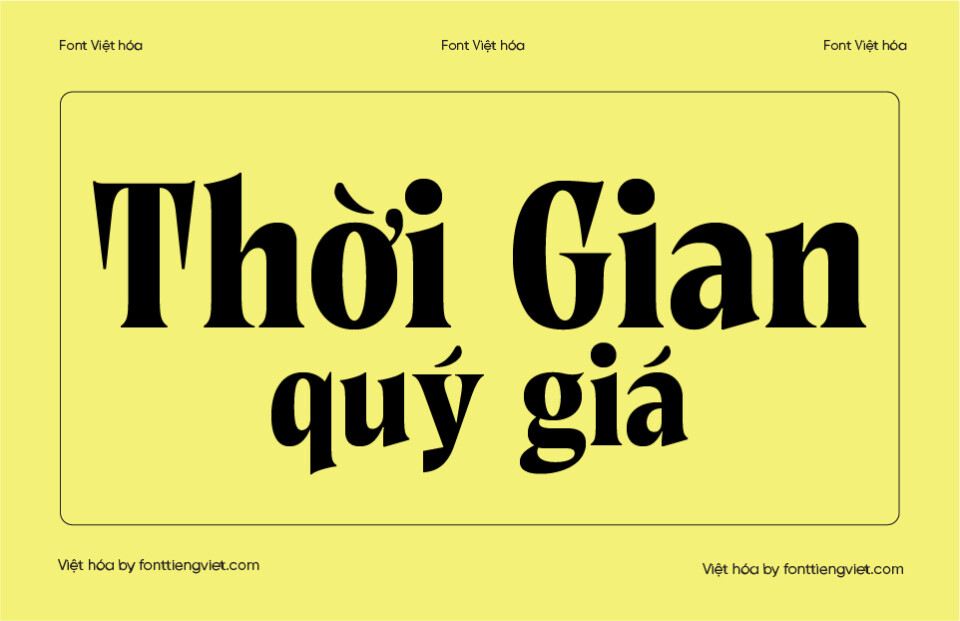
Font Việt hóa 1FTV VIP Ruminate Nuance
Font Việt hóa 1FTV VIP Ruminate Nuance – Đỉnh cao nghệ thuật thiết kế chữ chuyên nghiệp
Trong thế giới thiết kế đồ họa hiện đại, việc tìm kiếm một bộ font chữ đáp ứng được cả tiêu chí thẩm mỹ lẫn khả năng đọc hiểu là điều vô cùng quan trọng đối với các nhà sáng tạo. Font Việt hóa 1FTV VIP Ruminate Nuance nổi lên như một giải pháp hoàn hảo, mang đến sự kết hợp tinh tế giữa nét đẹp cổ điển và hơi thở đương đại. Đối với những bạn học sinh, sinh viên hay những người mới bắt đầu làm quen với lĩnh vực thiết kế, việc sở hữu một Font Miễn Phí chất lượng như thế này sẽ giúp nâng tầm các dự án bài tập, bài thuyết trình hay những ấn phẩm truyền thông cá nhân một cách đáng kể. Bộ font này không chỉ đơn thuần là các ký tự, mà còn là công cụ truyền tải cảm xúc và thông điệp một cách mạnh mẽ nhất thông qua từng đường nét được chau chuốt tỉ mỉ.
Khám phá vẻ đẹp độc đáo của Font Việt hóa 1FTV VIP Ruminate Nuance
Bộ font này được cộng đồng thiết kế đánh giá cao nhờ vào sự hài hòa giữa các nét thanh và nét đậm, tạo nên một cấu trúc chữ vững chãi nhưng không kém phần mềm mại. Đặc biệt, phiên bản Font Việt hóa 1FTV VIP Ruminate Nuance đã được tối ưu hóa hoàn toàn hệ thống dấu tiếng Việt, đảm bảo không xảy ra lỗi hiển thị khi soạn thảo văn bản dài. Điều này cực kỳ hữu ích cho môi trường học đường, nơi các bạn cần trình bày nội dung một cách mạch lạc và chuyên nghiệp nhất.
Tính ứng dụng đa dạng trong các dự án sáng tạo
Với phong cách Serif sang trọng pha lẫn chút phá cách, Font Việt hóa 1FTV VIP Ruminate Nuance cực kỳ phù hợp cho các thiết kế tiêu đề sách, bìa tạp chí hoặc các bài đăng trên mạng xã hội. Các đường chân chữ (serif) của bộ font này được vuốt nhọn tinh tế, tạo cảm giác thanh thoát và dễ nhìn trên cả màn hình máy tính lẫn bản in. Các bạn học sinh có thể sử dụng font này để thiết kế báo tường, làm slide thuyết trình PowerPoint để tạo ấn tượng mạnh mẽ với thầy cô và bạn bè. Ngoài ra, tính năng “Nuance” trong tên gọi của font còn ám chỉ sự biến chuyển nhẹ nhàng, giúp nội dung của bạn trở nên sâu sắc và có chiều sâu nghệ thuật hơn bao giờ hết.
Ưu điểm vượt trội khi sử dụng font chữ đã được Việt hóa
Lợi ích lớn nhất của việc sử dụng Font Việt hóa 1FTV VIP Ruminate Nuance chính là sự tiện lợi. Thay vì phải tốn thời gian chỉnh sửa từng dấu câu thủ công, người dùng có thể gõ tiếng Việt một cách tự nhiên với các bộ gõ phổ biến như Unikey hay Vietkey. Hơn nữa, font chữ này còn hỗ trợ đầy đủ các ký tự đặc biệt, giúp bạn tự do sáng tạo mà không bị giới hạn bởi rào cản kỹ thuật. Đây là lựa chọn lý tưởng cho những ai yêu thích sự hoàn mỹ trong từng chi tiết nhỏ của con chữ.
Hướng dẫn sử dụng Font Việt hóa 1FTV VIP Ruminate Nuance hiệu quả
Để phát huy tối đa vẻ đẹp của bộ font này, bạn nên kết hợp nó với các font chữ không chân (Sans-serif) đơn giản cho phần nội dung chính. Việc tạo ra sự tương phản giữa Font Việt hóa 1FTV VIP Ruminate Nuance ở phần tiêu đề và một font đơn giản ở phần thân bài sẽ giúp bố cục thiết kế trở nên cân đối, chuyên nghiệp hơn. Hãy chú ý đến khoảng cách giữa các chữ cái (kerning) để văn bản luôn giữ được sự thông thoáng và tinh tế cần thiết.